すべての人に読みやすく美しいUDフォント「UD明朝体」
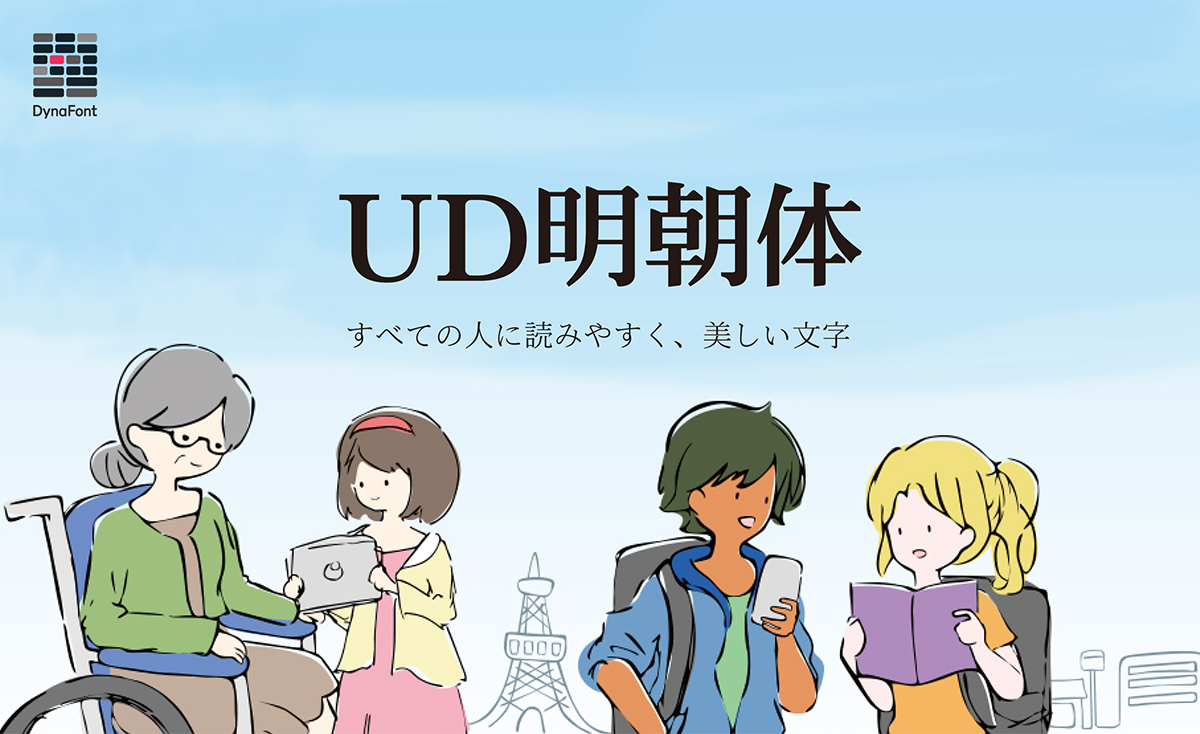
UD明朝体は、ユニバーサルデザイン(UD)をコンセプトにして視認性と可読性を高め、細部まで親しみやすいデザインにする事で、高齢者や弱視(ロービジョン)の人を含めて全ての人が読みやすいように開発された明朝体。
W2、W3、W4、W5、W6、W7の6書体でファミリー展開。
中国語UDフォント「UDゴシック体 繁体字中国語」「UDゴシック体 簡体字中国語」
「UDゴシック体 繁体字中国語」「UDゴシック体 簡体字中国語」は、ユニバーサルデザインをコンセプトに日本語フォントとして、先行開発した可読性・視認性・判読性に優れた「UDゴシック体」の中国語版フォント。
それぞれW2、W4、W6で展開。
UDゴシック体 繁体字中国語
繁体字中国語は、簡略化を経ていない筆画が多い漢字の字体体系。ユニバーサルデザインに基づいて開発された繁体字ゴシック体フォント。
UDゴシック体 簡体字中国語
簡体字中国語は、中華人民共和国で制定された従来の漢字を簡略化した字体体系。ユニバーサルデザインに基づいて開発された簡体字ゴシック体フォントとなる。
多言語フォント「金剛黒体クメール語」、「金剛黒体アルメニア語」、「金剛黒体ラオス語」
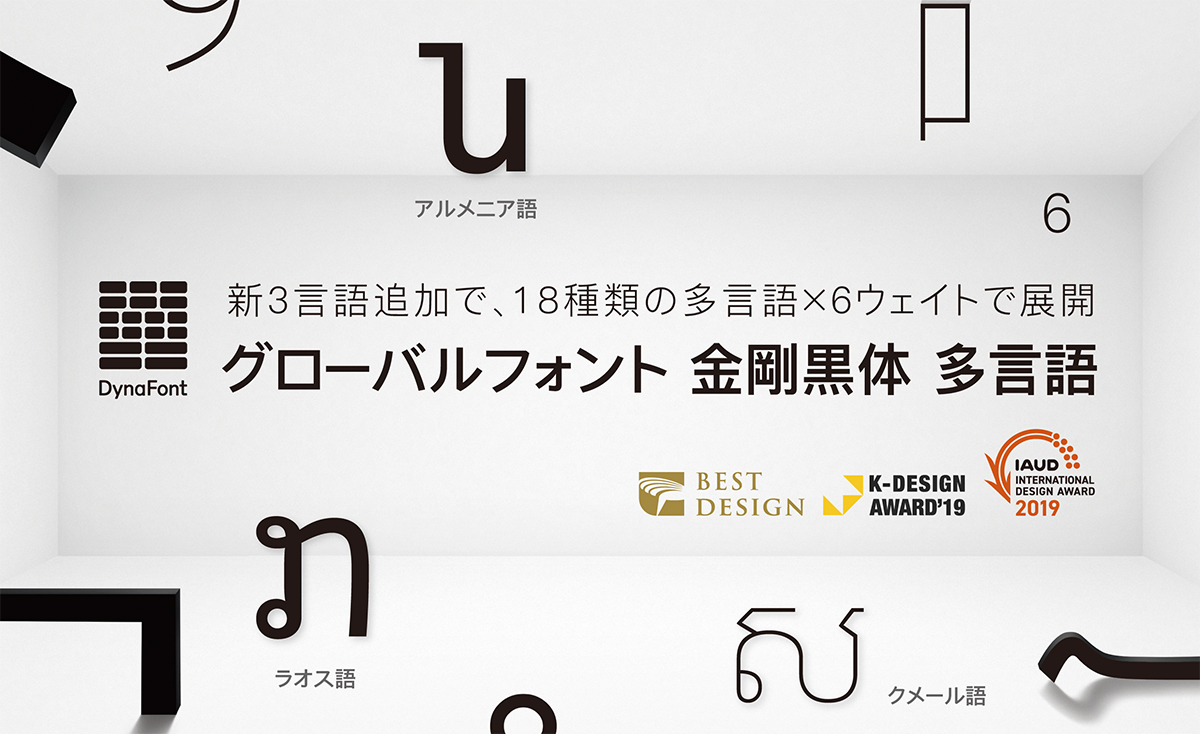
多言語フォント「金剛黒体クメール語」、「金剛黒体アルメニア語」、「金剛黒体ラオス語」は多言語フォント「金剛黒体」の新3言語。
これまでに発表している15種類の「金剛黒体 多言語」同様に、各言語の個性にあわせた書き方と書体として統一したデザインを採用。
それぞれUltralight、Thin、Light、Regular、Medium、Semiboldの6ウエイトでファミリー展開。
金剛黒体クメール語
クメール語はインドのブラーフミー系文字に由来しているとされ、カンボジアの公用語として使用されている。母音、子音、二重子音、独立母音といった要素で構成され、上下左右に組み合わせることができるという独特な特徴がある。
金剛黒体クメール語は、正確な書き方を保ちながらも独自の技術により、字母が異なる組み合わせになっても大きさや位置を柔軟に調整することができる。デザイン面では理性と感性のバランスを取り、細かい部分ではクメール文字の柔らかな曲線と幾何学的で左右対称の美しさがそのまま残されており、一部の文字でシンプルなデザインを採用し、すっきりと落ち着いた個性を引き出している。
金剛黒体アルメニア語
アルメニア文字は、ラテン語と同様に左から右に向かって書き進める表音文字で、字母は38文字あり、非常に古い表記システムで書かれる文字。現在、アルメニア語に似たような言語はなく、一般的にインド・ヨーロッパ語族の独立した一語派を形成。
金剛黒体アルメニア語は、ふところがしっかりと取られており、シンプルで爽やかなデザインが小さな文字を表示する場合でも優れた視認性を発揮。デザイン面では、ラテン語と一貫性を持たせながら、アルメニア文字の折れや曲げに見られる独特の書き方を残している。また、字間を調整し、余白部分を削ることで文字を組んだ時の視覚的なバランスを大幅に向上させている。
金剛黒体ラオス語
ラオス語は、ラオスの公用語やその他少数民族が使用している言語。タイ語に近く、美しいループと曲線が特徴的で、独特の風格が漂っている。
金剛黒体ラオス語は、金剛黒体シリーズの特長である字幅が広く、落ち着いたスタイルを継承。また、ラオス語を書く際の運筆を取り入れ、母語話者に指導と校正を依頼することでラオス語らしい滑らかで優雅な美しさを余すところなく表現した書体。
元号「令和」発表時の“令”の字形に対応した「楷書体 令和版」6書体
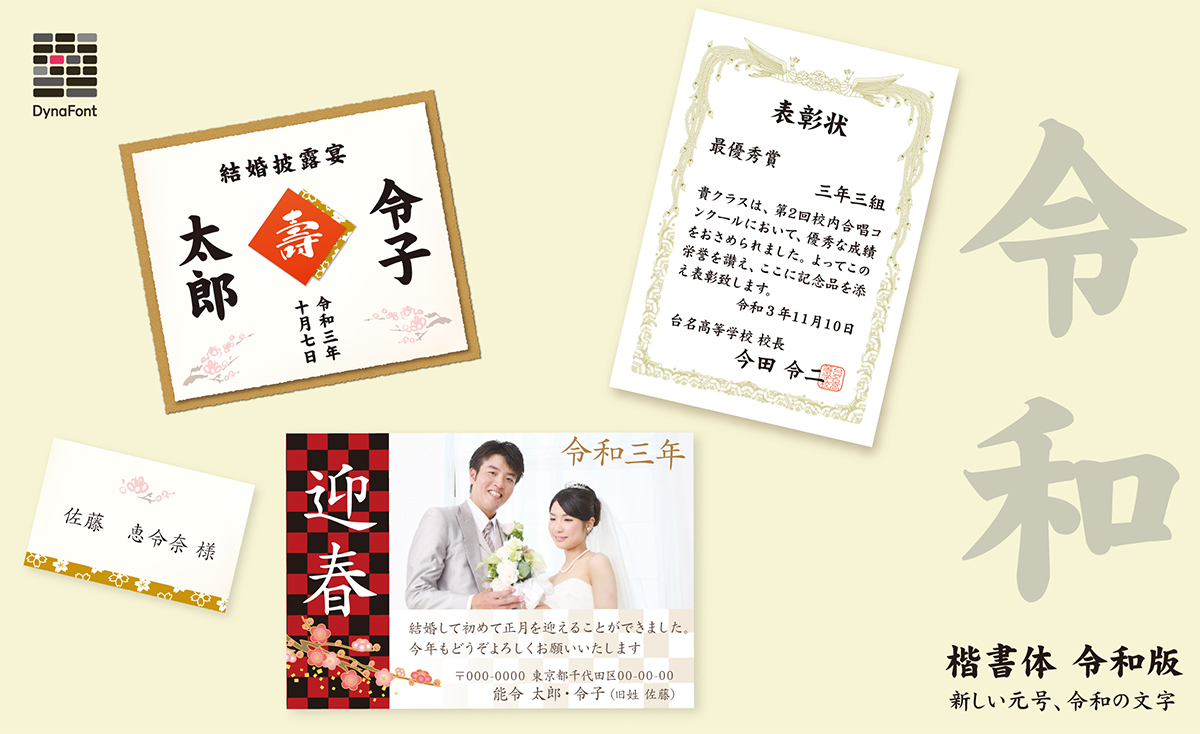
「楷書体 令和版」は、厳格な楷書体を現代でも使いやすいように視認性と判別性を高めたデザインの楷書でる細楷書体、中楷書体、中太楷書体、太楷書体、極太楷書体、超極太楷書体の6書体を元号「令和」発表時の“令”の字形に対応した書体。
「甲金文体」が異体字を追加し、300文字以上収録に
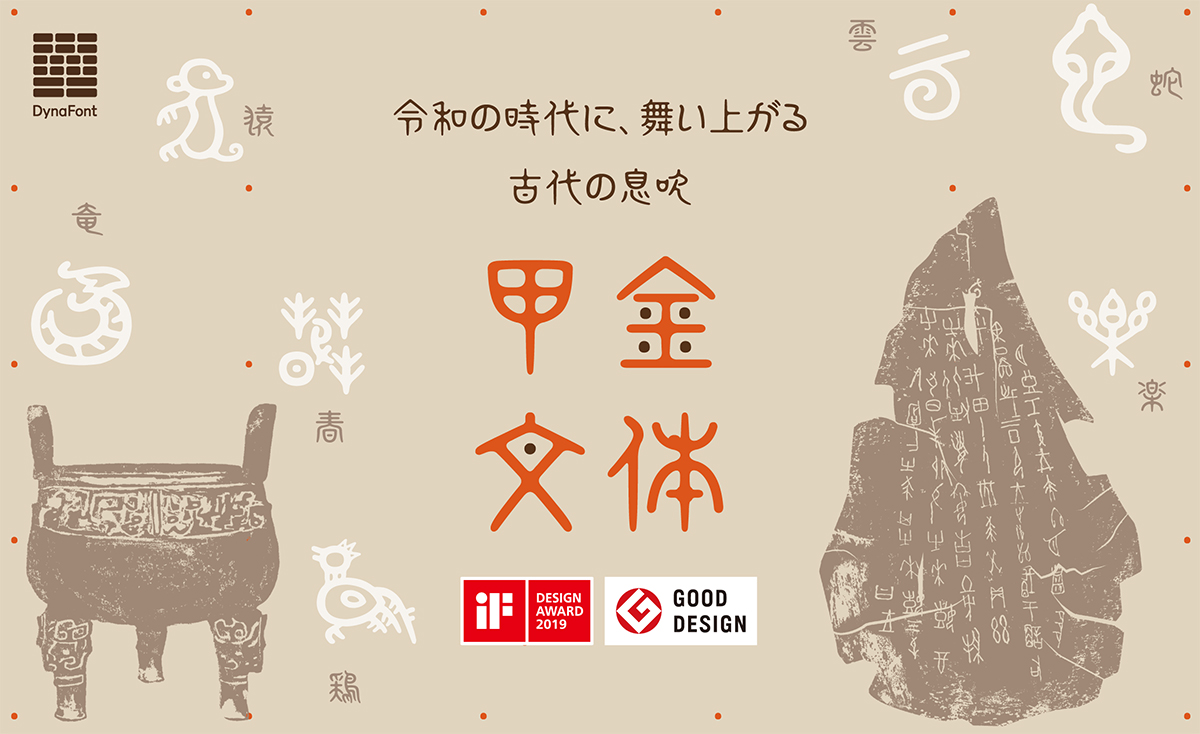
「甲金文体」は、古代文字の美しさに着目して甲骨文や金文体の特徴である幾何学的な模様を取り入れた素朴ながらも気品さも備えた書体。これまでの収録数である208文字の異体字からOpenType StdN版は325文字、TrueType Win版は316文字、TrueType Mac版には302文字の異体字が収録された。